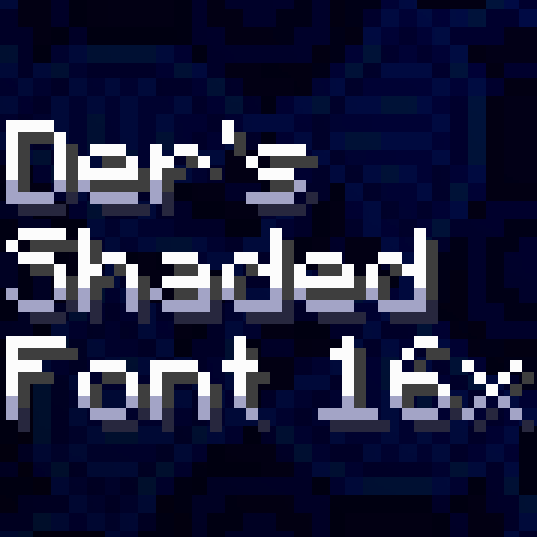
Der's Shaded Font Plus (Default 16x)
Ресурспак, который добавляет тени и подсветку к шрифту Майнкрафт. Поддержка более 11 000 символов, языков, стилей и популярных серверов вроде Hypixel и Wynncraft. Доступен для версий 1.6.1-26.2.
Der's Shaded Font Plus (Default 16x) - это текстурпак для Майнкрафт, который меняет стандартный шрифт игры, добавляя к каждому символу аккуратную цветную тень. Визуал становится свежее и приятнее для глаз - особенно если надоел ванильный плоский текст.
Что это и зачем нужно
В Майнкрафте шрифт всегда был довольно простым - никаких теней, никаких украшений. Этот ресурспак исправляет ситуацию: он добавляет цветную заливку к нижней части каждого символа. Буквы, цифры и даже спецсимволы выглядят объёмнее, без лишних эффектов.
Поддерживается более 11 000 символов - от обычных латинских букв до редких глифов, которые в ваниле вообще не используются.
Особенности
В последних версиях добавили:
• 8 500+ затенённых глифов на 37 страницах юникода
• Поддержку языков и символов
• Исправления для кривых глифов (например, ▚)
• Совместимость с Hypixel (символы) и Wynncraft (тултипы)
Стили и версии
У ресурспака есть несколько вариантов оформления:
• Reshaded (текущий) - v10.1+
• Classic - больше цвета, v1-v9.2, v13-legacy
• Vibrant - насыщенный, только v10
• Rose-tinted - розовый оттенок
• Light Greenish - зеленоватый
• Grayscale - чёрно-белый
• Opal/Pastel-✨ - пастельная радуга
• Subtle Default Gradient - лёгкий градиент
Функционал тоже разный:
• Без теней у иллюгеров - v1, v2 и v16
• Тултипы Wynncraft - v13+
• Символы Hypixel - v11+ (лучше v12+)
• Больше языков и юникода - v11+ (рекомендуется v12+)
• Зачарованные частицы с тенями - v17+
Важно знать
Некоторые символы при жирном начертании выглядят двойными - это особенность самого Майнкрафт, а не ресурспака. Такие глифы просто не затеняются, чтобы не было проблем.